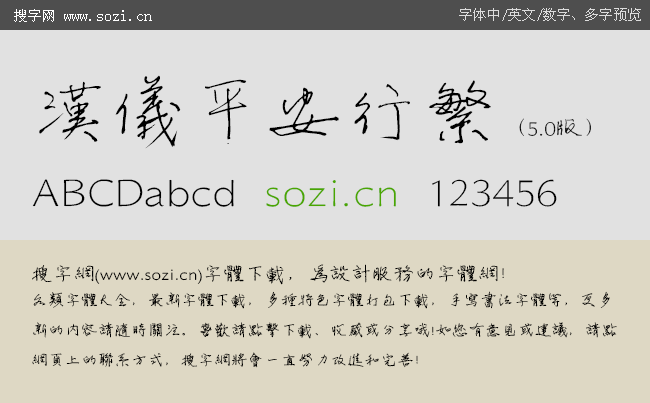
漢儀平安行繁
搜字網(wǎng)提供一款漢儀平安行繁體中文字體下載,漢儀平安行是一款字形纖細(xì)、整體灑脫飄逸的藝術(shù)字體,字體結(jié)構(gòu)大方、筆畫十分地瀟灑得體,效果十分出眾。使用漢儀平安行簡(jiǎn)制作出來的字體,有一種手寫體的味道,當(dāng)作簽名也是未嘗不可的,可以應(yīng)用于網(wǎng)頁或者活動(dòng)宣傳等領(lǐng)域。